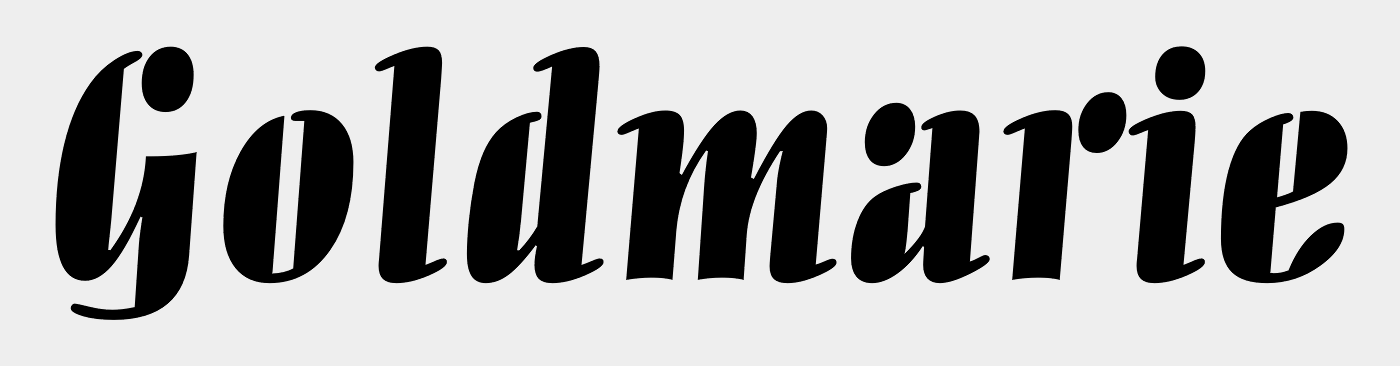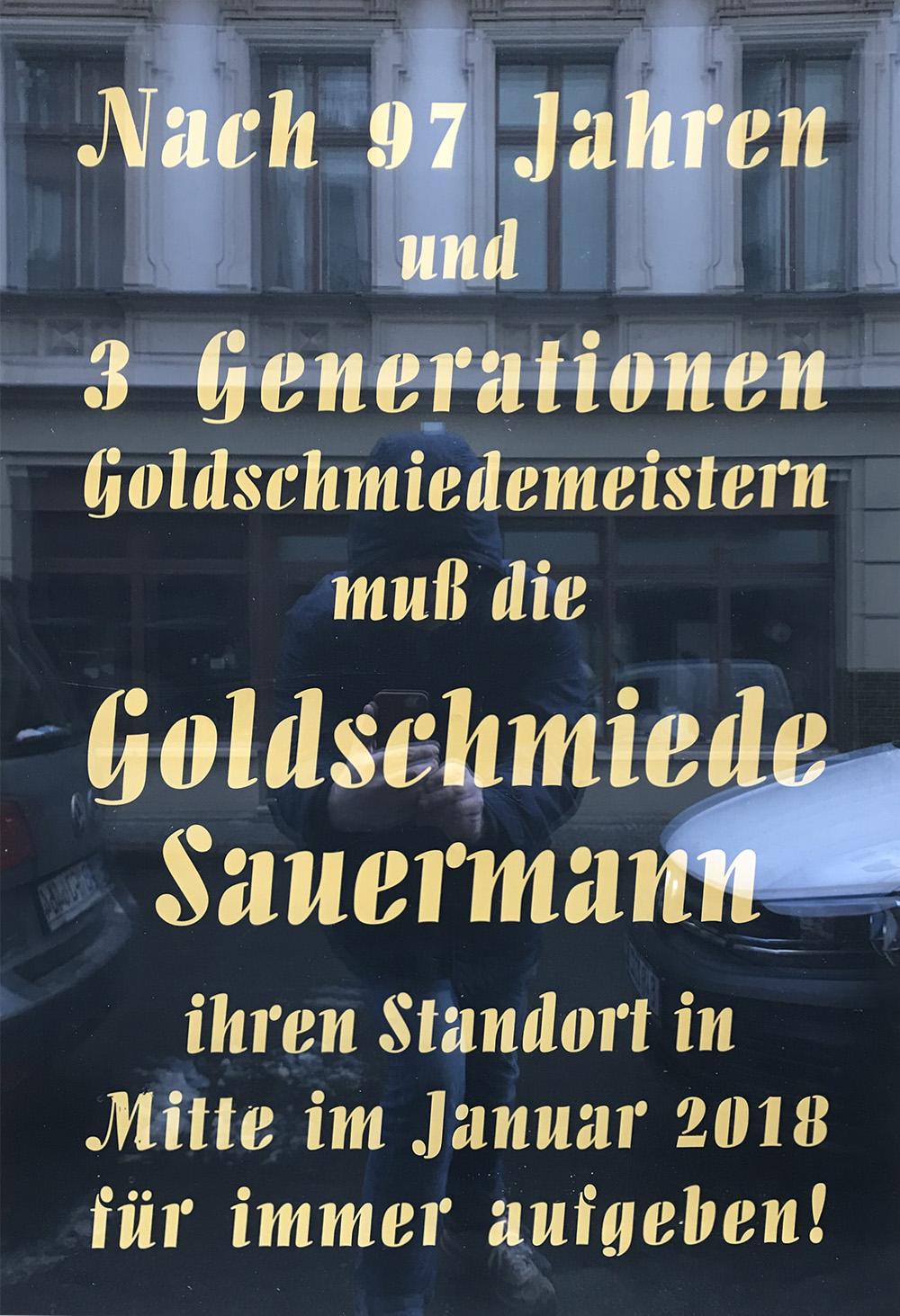
Suche Retro-Headlineschrift einer Goldschmiede
Der Laden befindet sich in Berlin-Mitte in der Mulackstraße. Die Schrift kommt mir bekannt vor aber die bisherige Suche war leider erfolglos.